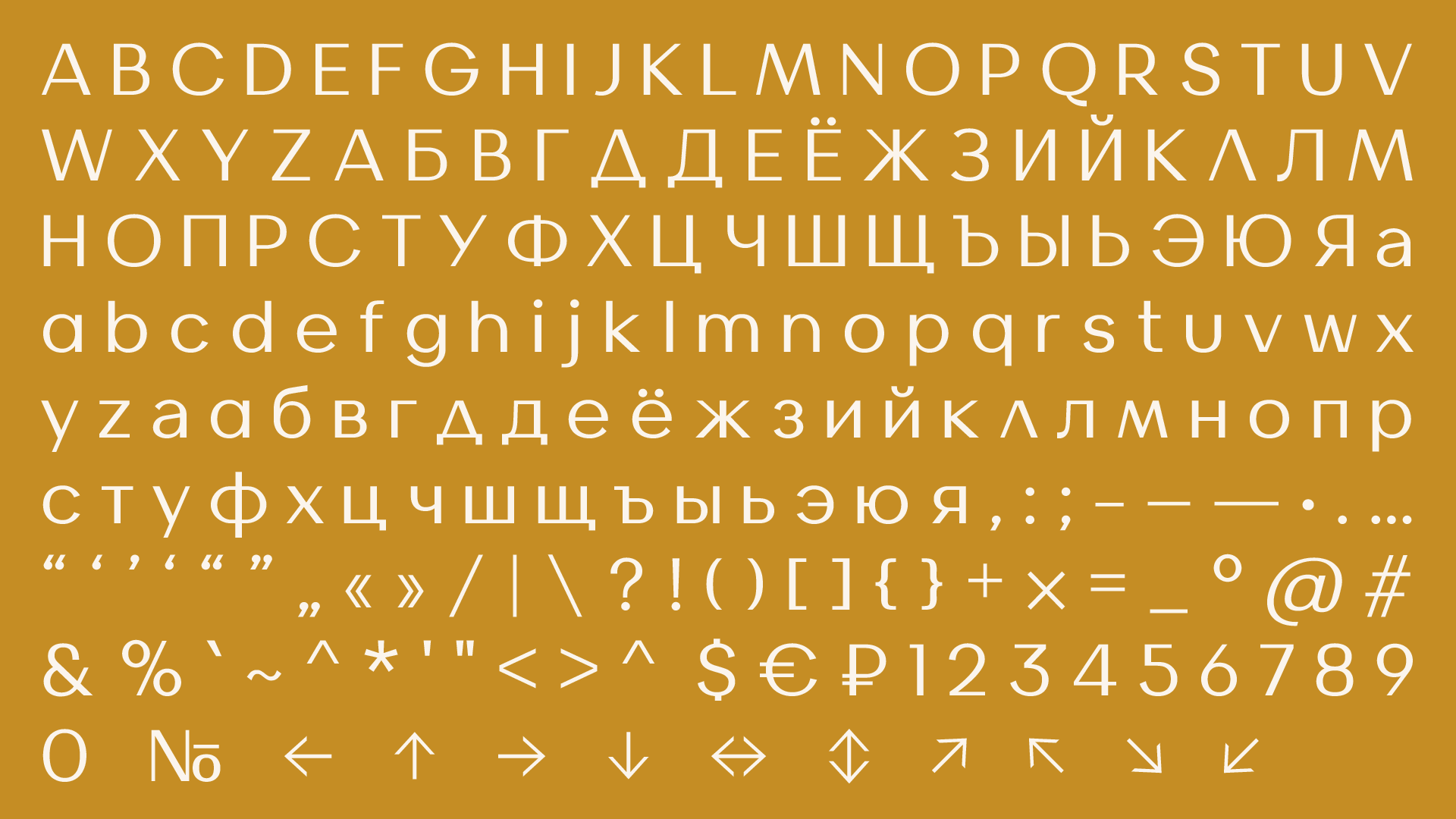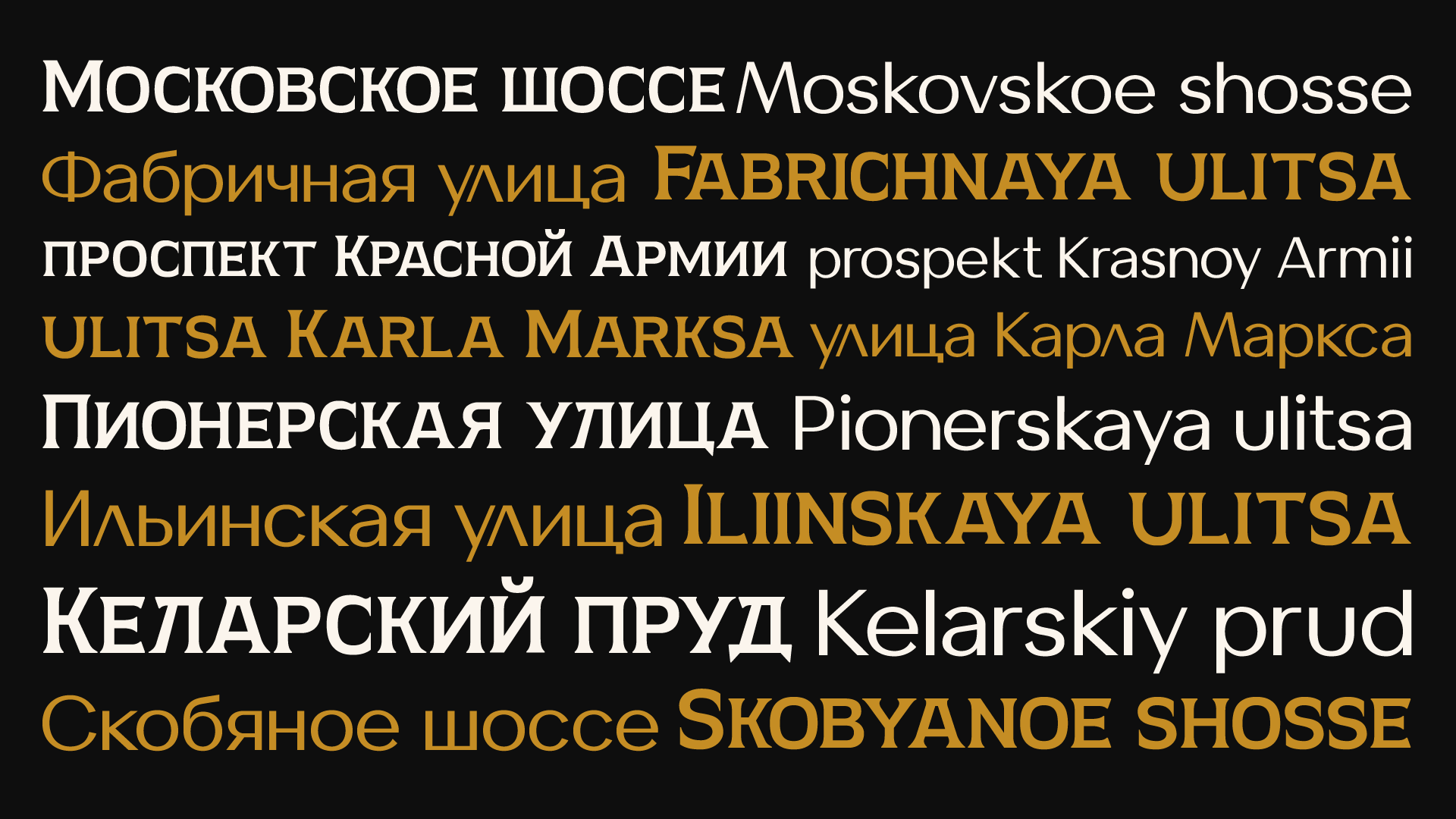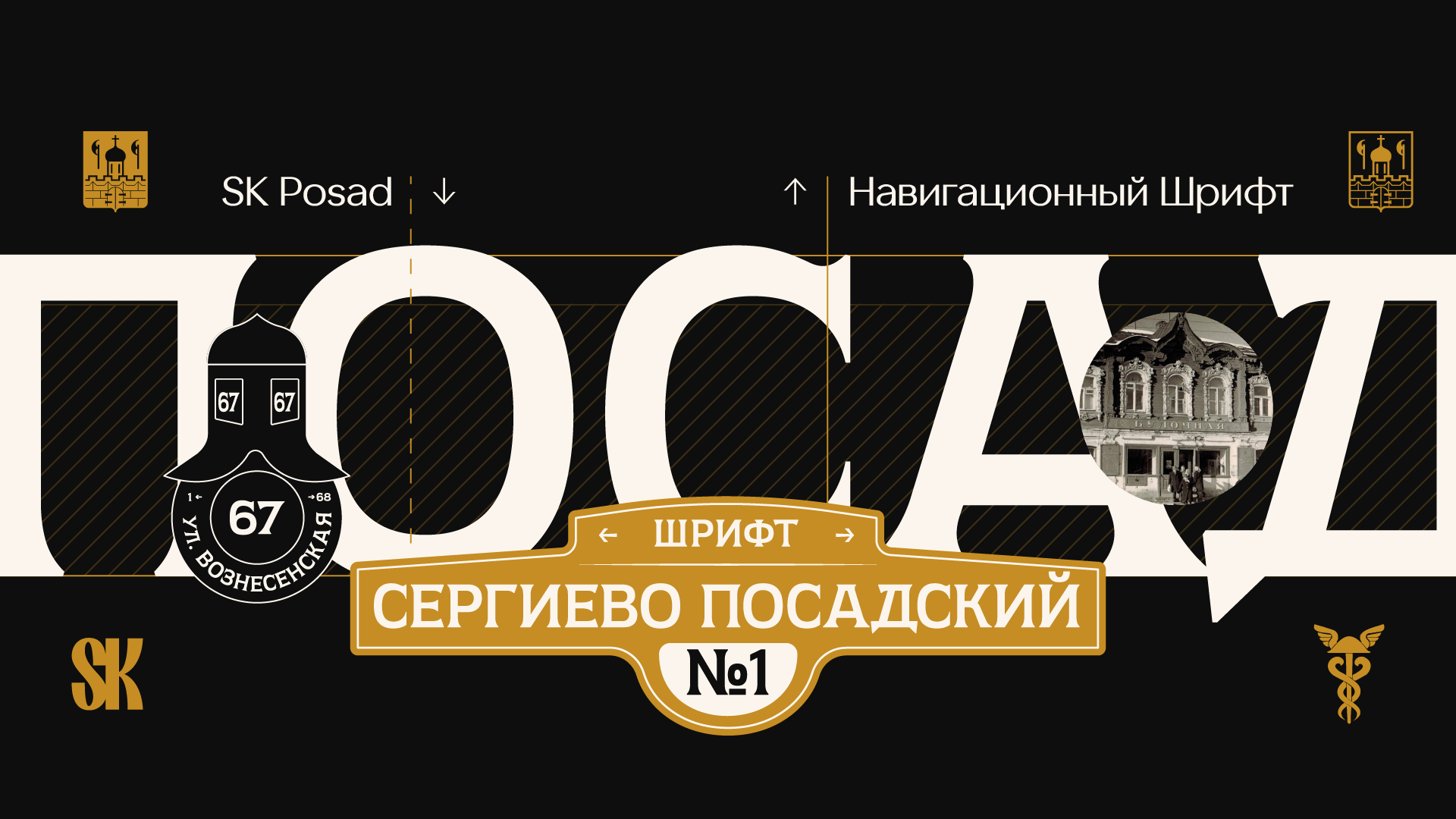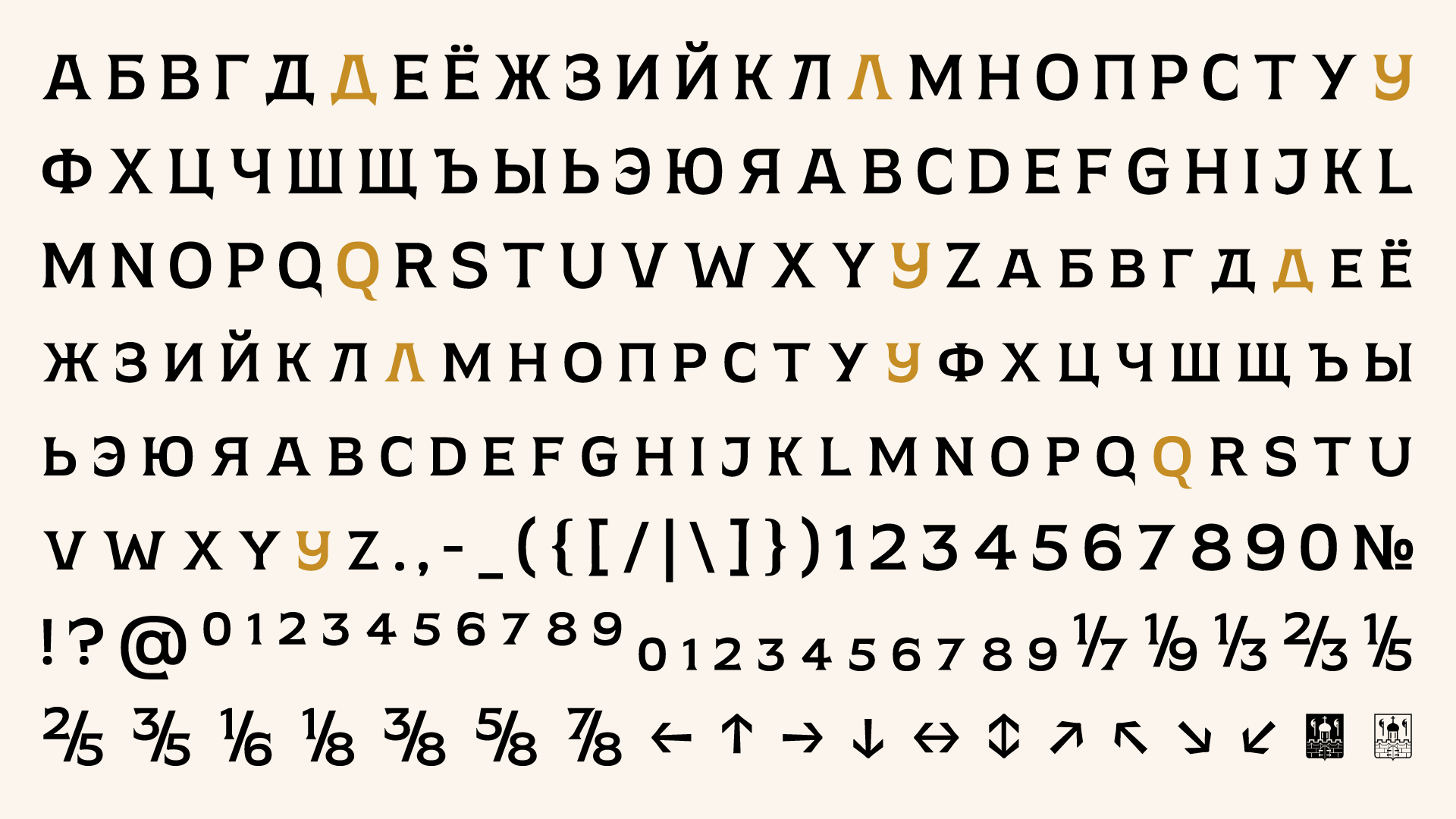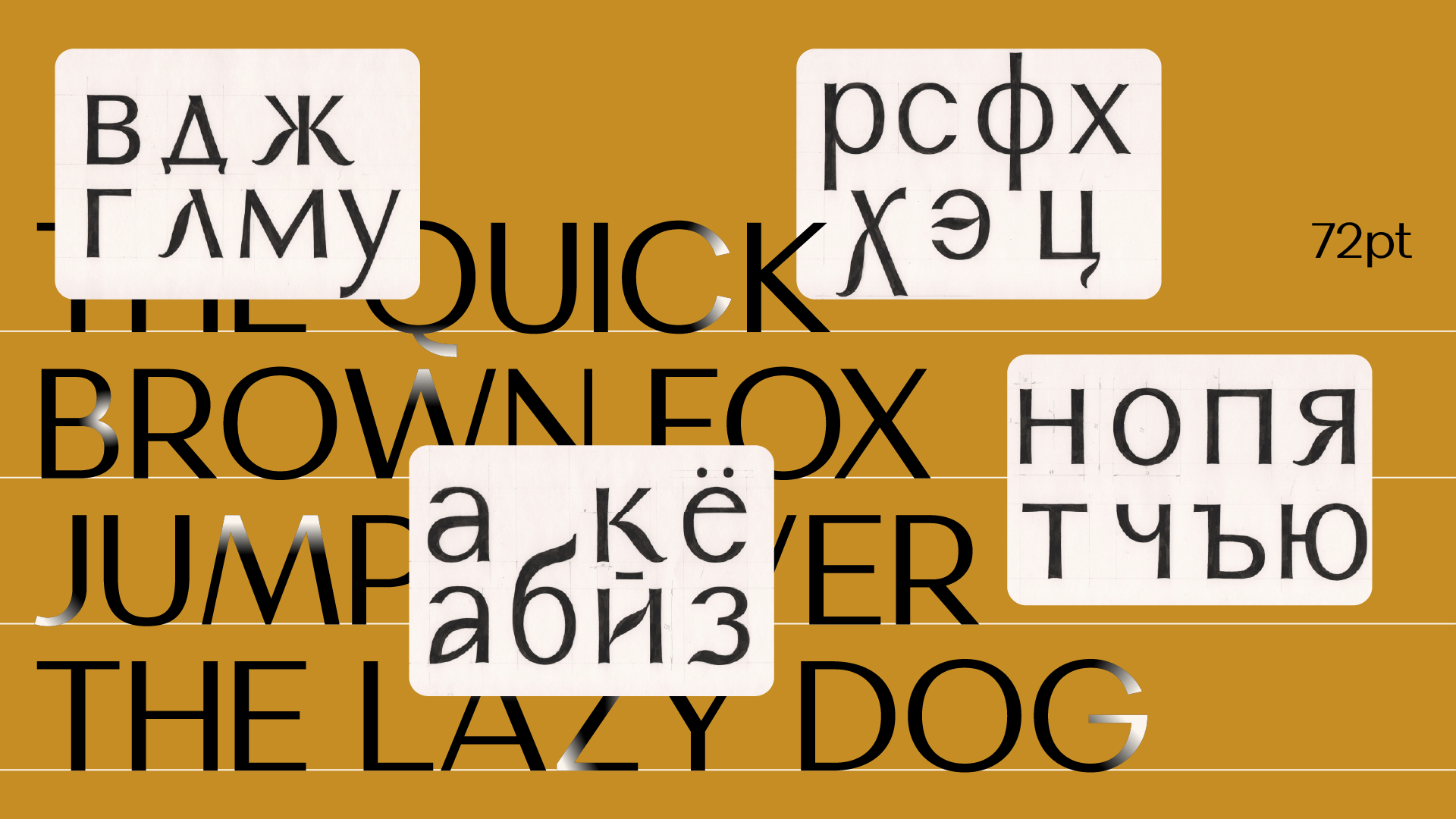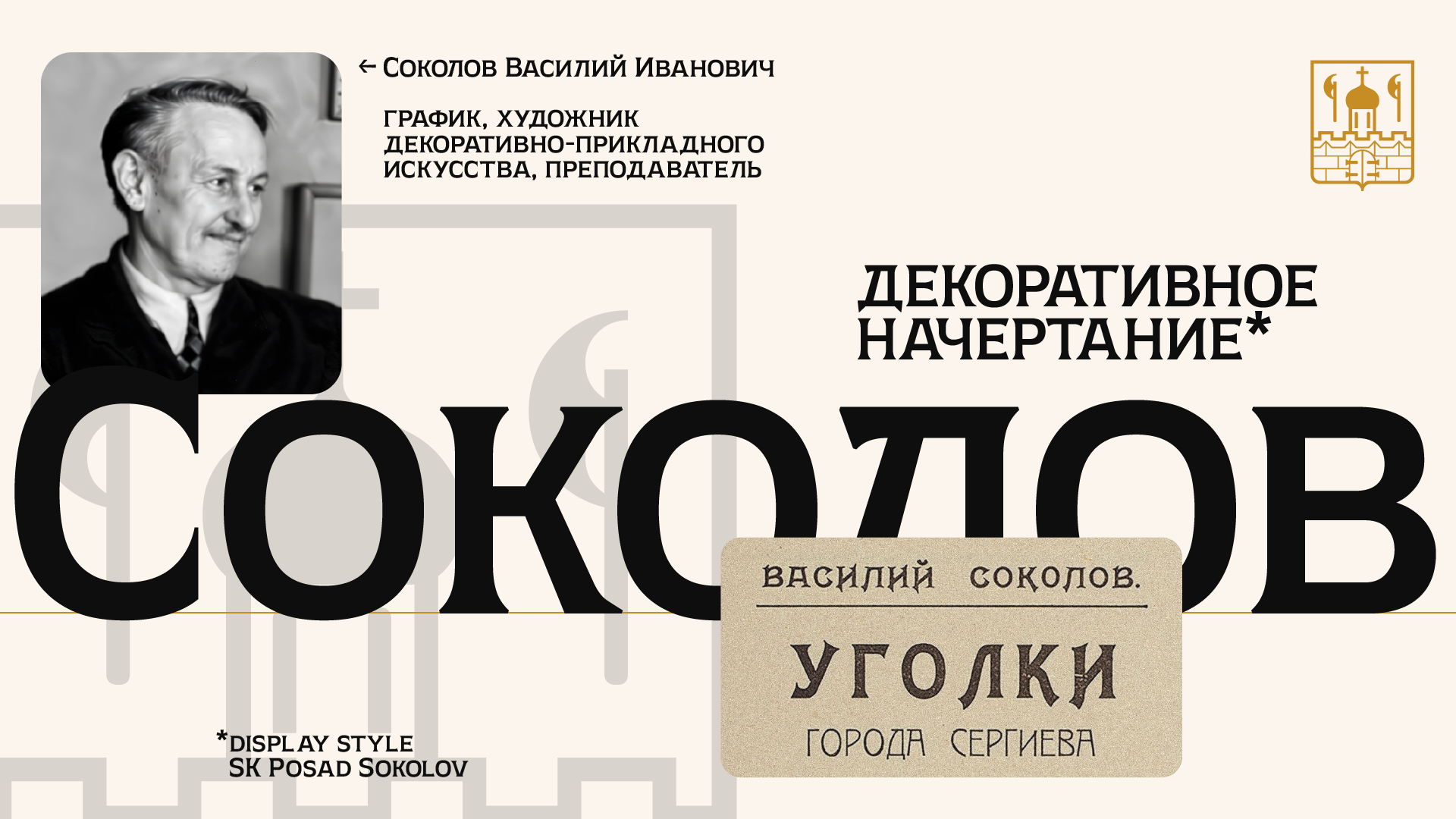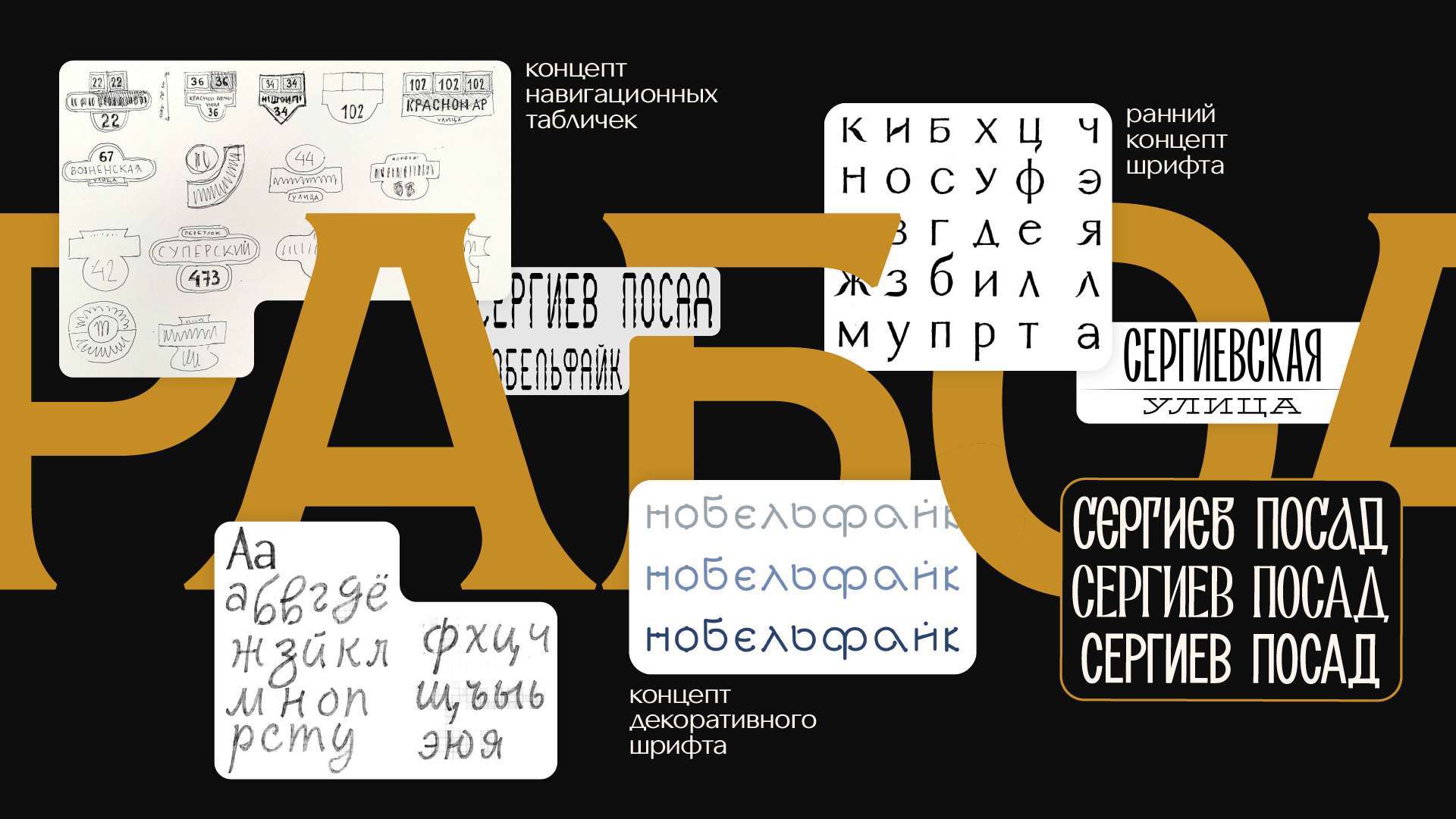
SK Posad — Навигационный шрифт Сергиева Посада.
SK Posad — это навигационный шрифт для Сергиева Посада в двух начертаниях: для вывесок, плакатов и аншлагов; для документов, карт и текстов. Он был создан совместно с активными жителями города на серии воркшопов, организованных городской администрацией.
SK Posad Sokolov — декоративное начертание шрифта, созданное для вывесок, афиш и плакатов Сергиева Посада. Его дизайн вдохновлён дореволюционной типографикой и эстетикой купеческих предприятий, отражая историческую идентичность и визуальную культуру города.
SK Posad Favorskiy — начертание разработанное специально для текстов, документации и, городской навигации Сергиева Посада. Оно вдохновлено шрифтовым наследием Владимира Фаворского, сочетает лаконичность современного дизайна с отсылки к культурным традициям города.